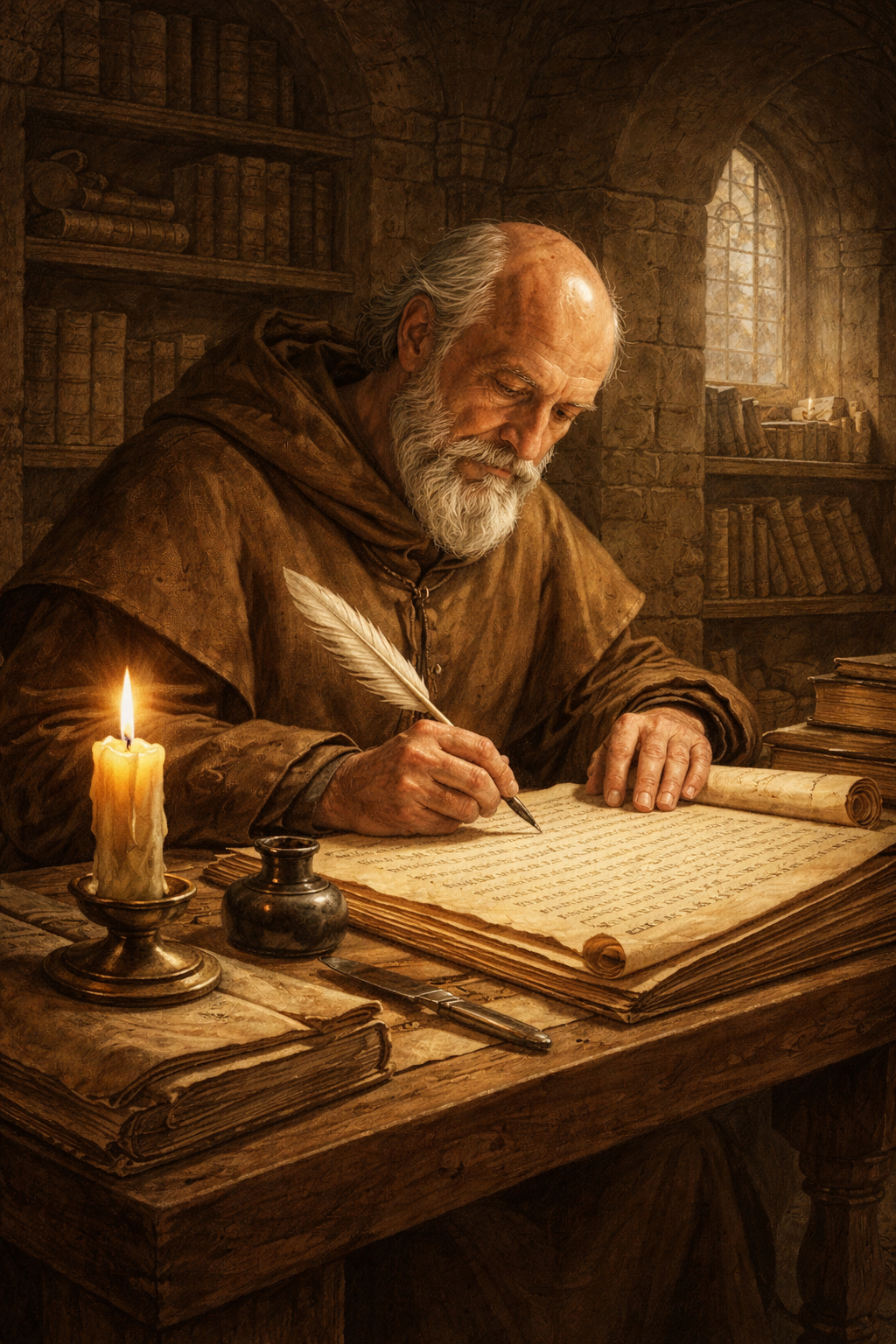
lädt Sie ein, sich dem Thema Schrift zu nähern. Egal ob in der Präsentation, der Ausstellung oder bei den Aktionstagen, an denen unter anderem auch alte Schreibtechniken selbst ausprobiert werden können, Vorträge über die Entwicklung der Schrift, vorrangig in Deutschland, gehalten werden und viel über das verbindende Medium der Schrift gelernt werden kann.